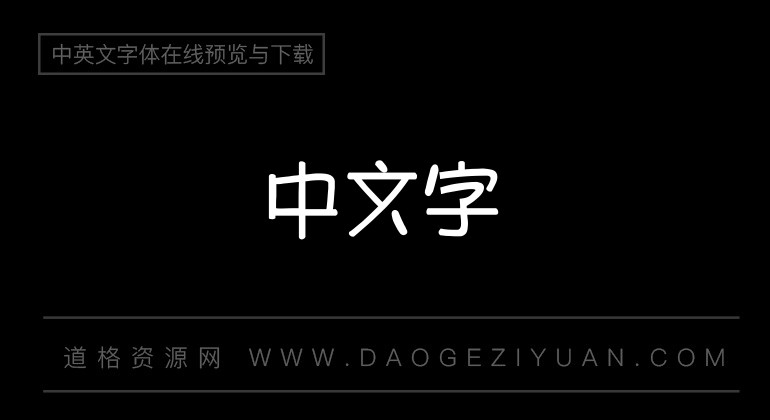
金梅美工广告字体
金梅美工广告字体是一款专为广告设计师量身打造的字体,它采用了现代简洁的设计风格,字体拥有独特的抽象感,表达出一种新颖的美感。它的字形简洁大方,且非常容易被识别,是一款非常适合用于广告设计的字体。
金梅美工广告字体是一款非常不错的手写艺术字体,具有很好的视觉感,适合于文化类的宣传设计、商业类品牌的广告和产品包装设计以及个性化文字排版等较多场景。